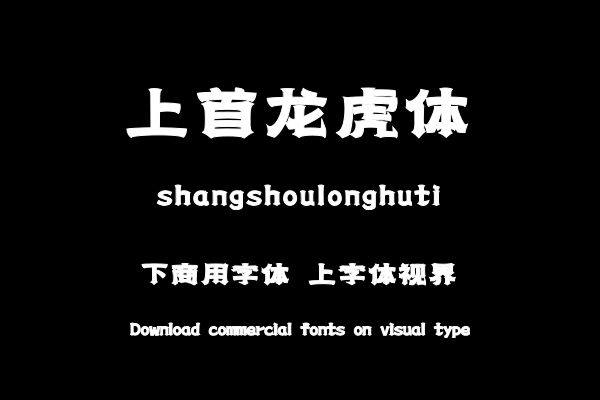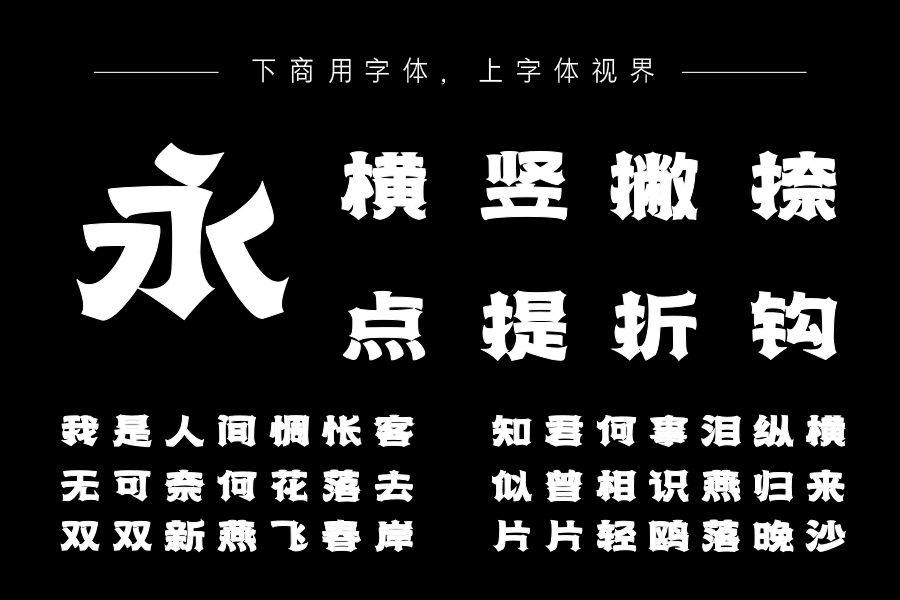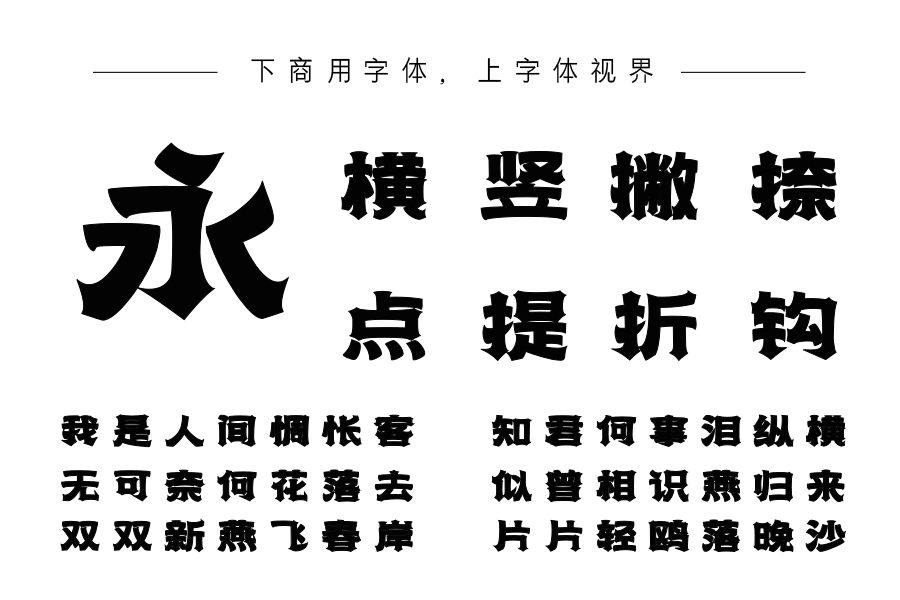
上首龙虎体,字体结合宋体进行风格化创新,笔画规整有序。结构统一,既保持了视觉上的美感,又添加了新元素,使字体更加生动有趣。购买须知:“下载服务费”与“字体VIP”所获得字体 仅用于个人非商用, 商用请联系付费授权。本字体为电脑用字,手机没有root权限不支持直接手机换字(手机如何root,请自行百度搜索教程)。购买前请先 了解清楚后再付款 ,字体为虚拟产品无法回收 一旦购买不支持退款。